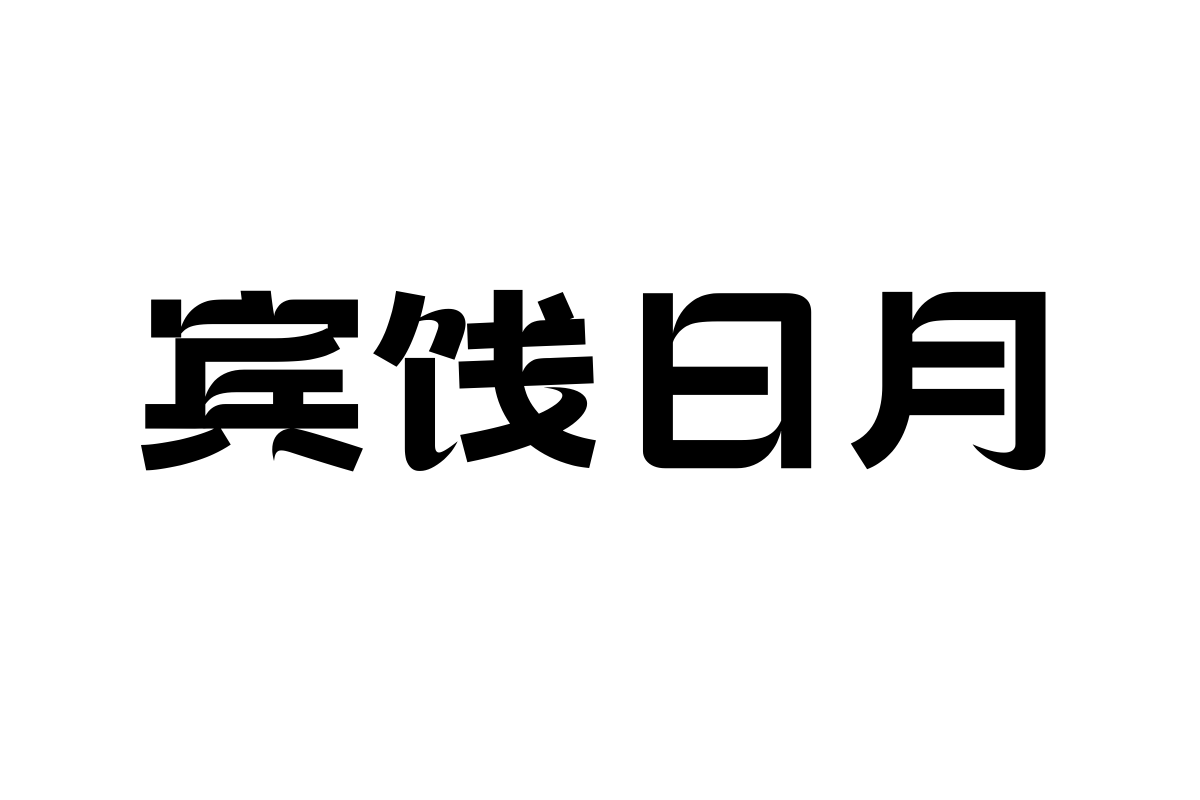
上首幻灵体是一款具有独特艺术风格的字体,它融合了现代与古典的元素,创造出一种独特的视觉体验。这款字体的特点是笔画流畅,结构紧凑,既有传统的书法韵味,又不失现代感。它的线条粗细变化丰富,既有粗犷的笔触,又有细腻的勾勒,给人一种既古朴又现代的感觉。同时,这款字体的字形结构也相当独特,有的字形呈现出优美的曲线,有的则显得简洁有力。总的来说,上首幻灵体是一款非常具有艺术性和观赏性的字体,适合用于各种需要表现艺术气息的场合。